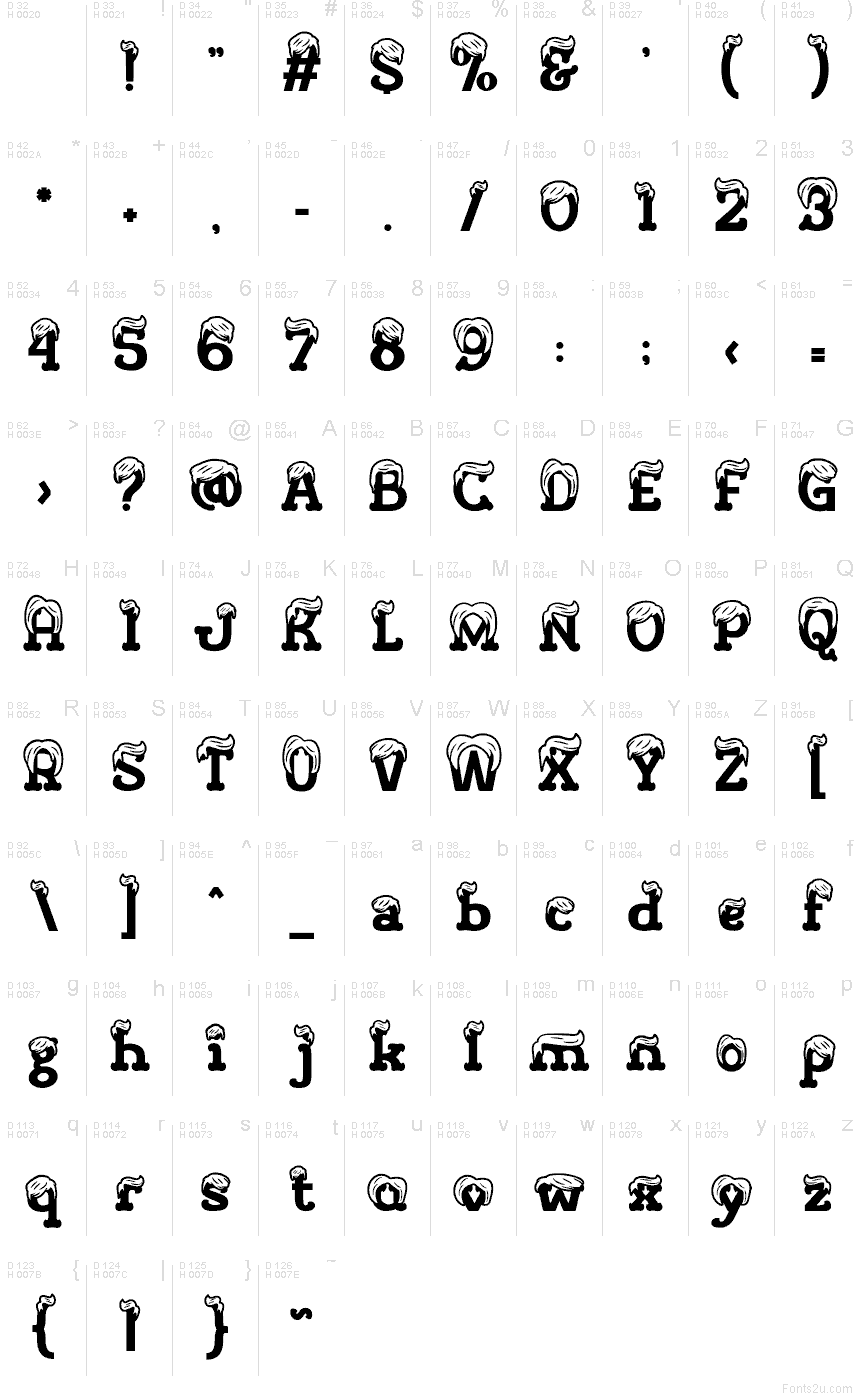
Visage Face Nine von Putracetol Studio ist eine kostenlose, surreale Display-Schrift mit einem Hauch von Cartoon-Gothic. Die Buchstaben wirken wie schwarze Silhouetten, die voluminöse, geschwungene Frisuren tragen. Die Kombination aus massiven unteren Formen und glänzenden, fein gekämmten Highlights verleiht dem Alphabet einen charaktervollen und wunderbar eigenwilligen Look, der perfekt für Poster geeignet ist.
Diese Mischung passt ideal zu Albumcovern, Horror-Comedy-Branding, Event-Postern, Aufkleber-Designs und Titelkarten, bei denen eine kostenlose Schrift die Stimmung ganz allein tragen muss. Sie funktioniert auch hervorragend für kurze Überschriften und Monogramme, da die haarartigen Oberseiten und die schweren Unterseiten selbst wenigen Buchstaben genug Präsenz verleihen, um gleichermaßen als Bild wie als Schrift wahrgenommen zu werden.
Visage Face Nine